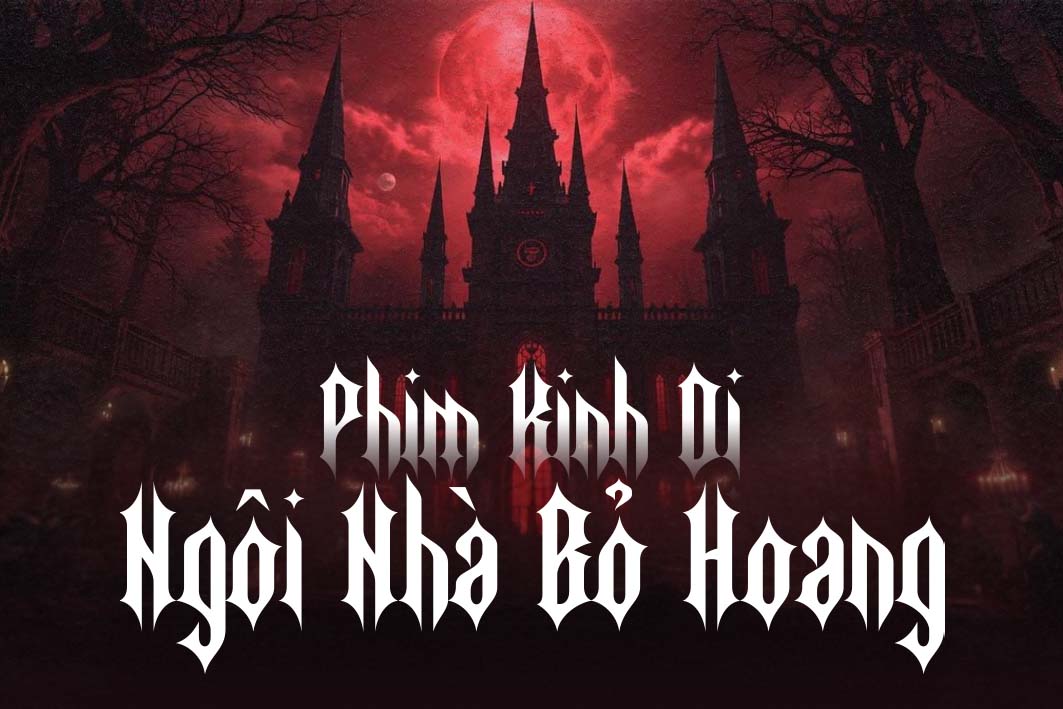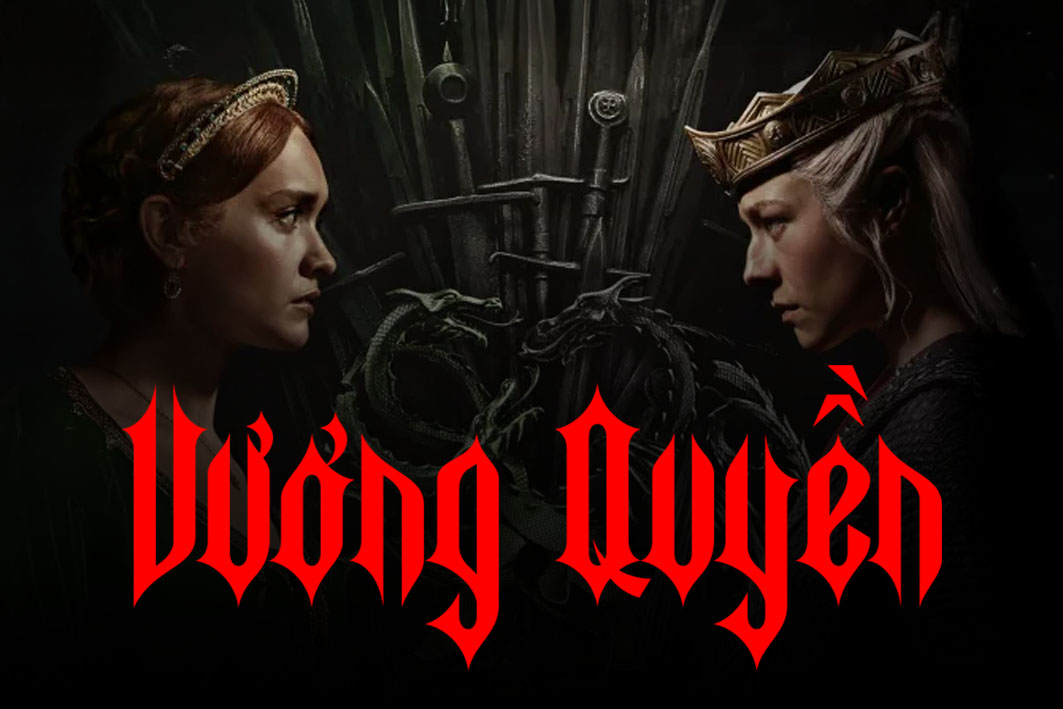
Font Kinh Dị Đậm Chất Gothic TH Modirgan Việt Hóa
Trong thế giới thiết kế đồ họa, việc lựa chọn typography phù hợp quyết định đến 80% cảm xúc của tác phẩm. Đặc biệt, khi mùa lễ hội hóa trang đang đến gần hoặc khi thực hiện các dự án mang màu sắc u tối, các designer luôn "săn lùng" những bộ font chữ halloween độc đáo để tạo điểm nhấn thị giác mạnh mẽ. Hôm nay, hãy cùng khám phá TH Modirgan – một siêu phẩm Gothic Display đã được Việt hóa hoàn chỉnh.
Vẻ đẹp ma mị của Modirgan
Modirgan là "đứa con tinh thần" của tác giả Rantau, một cái tên nổi bật trên thị trường tài nguyên đồ họa Envato Elements. Ngay từ cái nhìn đầu tiên, Modirgan đã gây ấn tượng bởi cấu trúc Gothic cổ điển nhưng được cách điệu với những đường nét sắc lẹm, gai góc.
Đây là sự lựa chọn hoàn hảo cho các chủ đề cần sự bí ẩn và kịch tính. Không giống như các typeface tròn trịa thông thường, Modirgan mang lại cảm giác lạnh lẽo, sắc bén, xứng đáng là một font chữ rùng rợn (dùng dợn) tiêu chuẩn cho các poster phim kinh dị, bìa sách trinh thám hay các ấn phẩm truyền thông mang phong cách Darkwear/Metal.
Tại sao nên chọn bản Việt hóa TH Modirgan?
Mặc dù bản gốc Modirgan rất đẹp, nhưng rào cản lớn nhất đối với designer Việt chính là việc thiếu hỗ trợ các ký tự có dấu. Hiểu được nhu cầu đó, Team TH đã thực hiện Việt hóa bộ phông này với tên gọi TH Modirgan.
Điểm nổi bật của bản Việt hóa này bao gồm:
* Dấu tiếng Việt chuẩn xác: Các dấu mũ, dấu thanh được Team TH vẽ lại tỉ mỉ, đảm bảo không bị chồng chéo hay lạc quẻ so với tổng thể các ký tự gốc.
* Kerning tối ưu: Khoảng cách giữa các ký tự được tinh chỉnh để văn bản hiển thị mượt mà nhất ngay cả khi gõ tiếng Việt.
* Giữ nguyên hồn cốt: Mọi chi tiết xước, gãy khúc tạo nên chất font chữ kinh dị đặc trưng của bản gốc đều được bảo toàn trọn vẹn.
Ứng dụng thực tế
TH Modirgan không chỉ giới hạn ở các thiết kế in ấn. Bạn hoàn toàn có thể sử dụng bộ font này cho:
- Tiêu đề video Youtube chủ đề tâm linh, khám phá bí ẩn.
- Logo và nhận diện thương hiệu cho các Studio game, Escape Room.
- Thiết kế áo thun, Merchandise phong cách Rock/Gothic.
Lời kết
Nếu bạn đang tìm kiếm một công cụ để "thổi hồn" vào những thiết kế mang sắc thái u tối, TH Modirgan chính là mảnh ghép còn thiếu trong kho tài nguyên của bạn. Sự kết hợp giữa tư duy thẩm mỹ của Rantau và sự chỉn chu của Team TH đã tạo nên một bộ font chất lượng, sẵn sàng thách thức mọi ý tưởng táo bạo nhất.